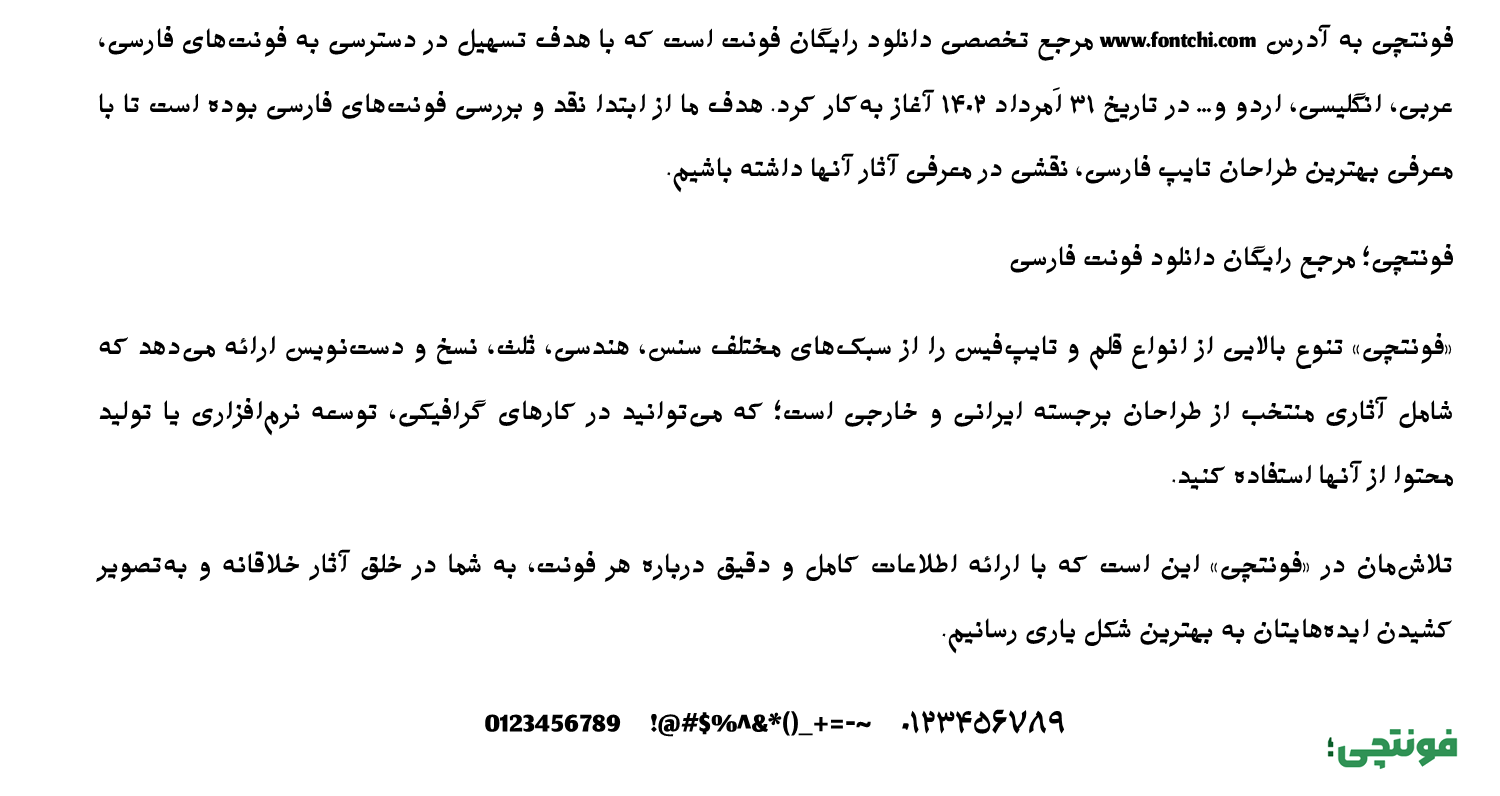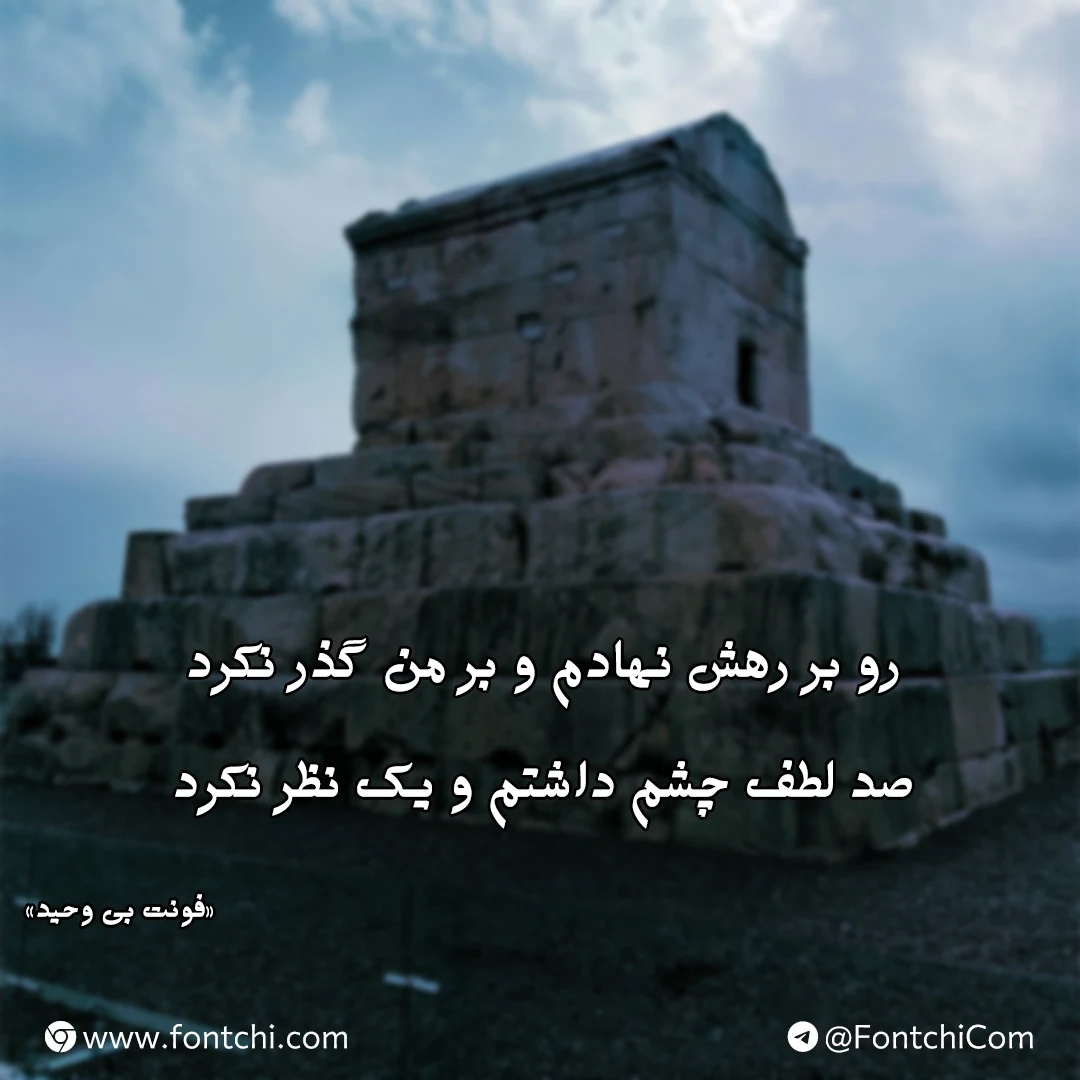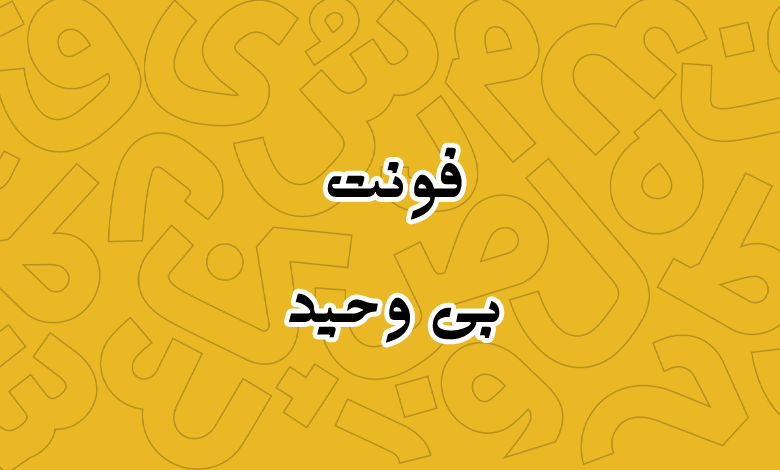
فونت بی وحید (B Vahid)
| نام | بی وحید |
| نام نمایشی | B Vahid |
| طراح | برنا رایانه |
فونت بی وحید یا وحید (به انگلیسی: B Vahid) از سری فونتهای B با ساختاری فانتزی است که با ظاهر برجسته و کلاسیک خود برای استفاده در متون کوتاه و عناوین کاربرد دارد. فونت بی وحید رایگان است و در یک وزن بولد ارائه شده است.
شرکت برنا رایانه این قلم را در دهه هفتاد شمسی با ظاهری نسبتا هندسی تولید کرده است که از سبک نقطهگذاری پیوسته پشتیبانی میکند. همچنین ظاهری صمیمی دارد که برای استفاده در شبکههای اجتماعی و عکسنوشته نیز کاربردی است.
فونت بی وحید با الهام از خطوط سنتی فارسی و با هدف ارائه ظاهری مدرن و کاربردی طراحی شده است. نسخه بولد این فونت، با ضخامت سیاه و تأکید بر خوانایی، برای استفاده در عناوین، تبلیغات و پروژههای گرافیکی که نیاز به جلب توجه دارند، بهینه شده است.
با اینکه فونت ظاهری سیاه و بولد دارد، اما در اندازههای بزرگتر مانند چاپ روی بنر، بیلبوردهای تبلیغاتی و عناوین با اندازه بزرگتر خود را بهتر نشان میدهد. اما به این معنی نیست که در ابعاد کوچک کاربردی نباشد.
فونت B Vahid علاوه بر زبان فارسی از زبان عربی نیز پشتیبانی میکند. زبان انگلیسی در این فونت فاقد گلیفها و حروف لاتین است و از فونت پیشفرض سیستم عامل برای این زبان استفاده خواهد شد. اگر به دنبال فونت جایگزین با این سبک هستید، میتوانید از قلمهایی با ظاهر سیاه استفاده کنید که پیش از این در صفحه لیست فونتهای انگلیسی معرفی کردهایم.
لازم به ذکر است که این فونت فارسی مشابه با اکثر فونتهای سری بی فاقد گلیف استاندارد برای اعداد عربی «٤٥٦» بوده و از همان اعداد فارسی «۴۵۶» مشابه با پیشنمایش استفاده میشود. از کاربردهای دیگر این فونت میتوان به موارد زیر اشاره کرد:
- تبلیغات و بیلبوردها: این فونت به دلیل ضخامت و جلبتوجه بالا، برای طراحی بنرها، بیلبوردها و پوسترهای تبلیغاتی بسیار مناسب است.
- عناوین و سرتیترها: در مجلات، روزنامهها و وبسایتها، بی وحید بولد بهعنوان فونتی برای عناوین و سرتیترها، توجه مخاطب را بهسرعت جلب میکند.
- طراحی گرافیک دیجیتال: از این فونت میتوان در طراحی پستهای شبکههای اجتماعی، تامنیلها و حتی زیرنویس ویدئوها استفاده کرد.
- اسناد رسمی و سربرگها: بی وحید بولد به دلیل ظاهر رسمی و در عین حال ساده، برای سربرگهای اداری و نامهنگاریهای حرفهای مناسب است.
یکی از بیشترین کاربردهایی که این فونت در دهههای اخیر داشته در صنعت چاپ همچون چاپ کارت عروسی است که همچنان نیز از آن استفاده میشود.